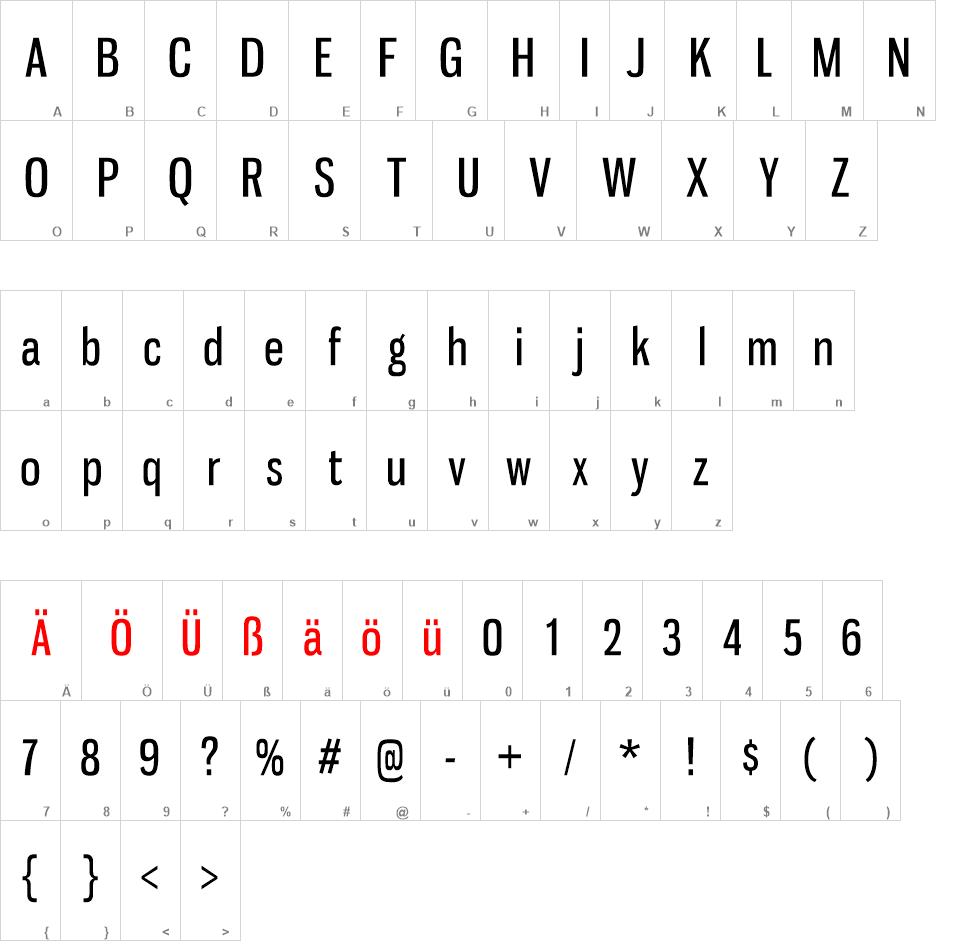
Gnuolane
Gnuolane font
Gnuolane
Gnuolane ist eine ernsthafte Schlagzeile in fünf Gewichten. Während es sich an Grotesken aus dem 19. Jahrhundert anlehnt, besitzt es ein superelliptisches Sechziger-Grinsen. Gnuolane enthält altmodische Zahlen, Ordinalzahlen, Vorgesetzte, Untergeordnete, f-Ligaturen und klassenbasiertes Kerning. Schauen Sie sich auch Gnuolane Jump & Gnuolane Stencil an.